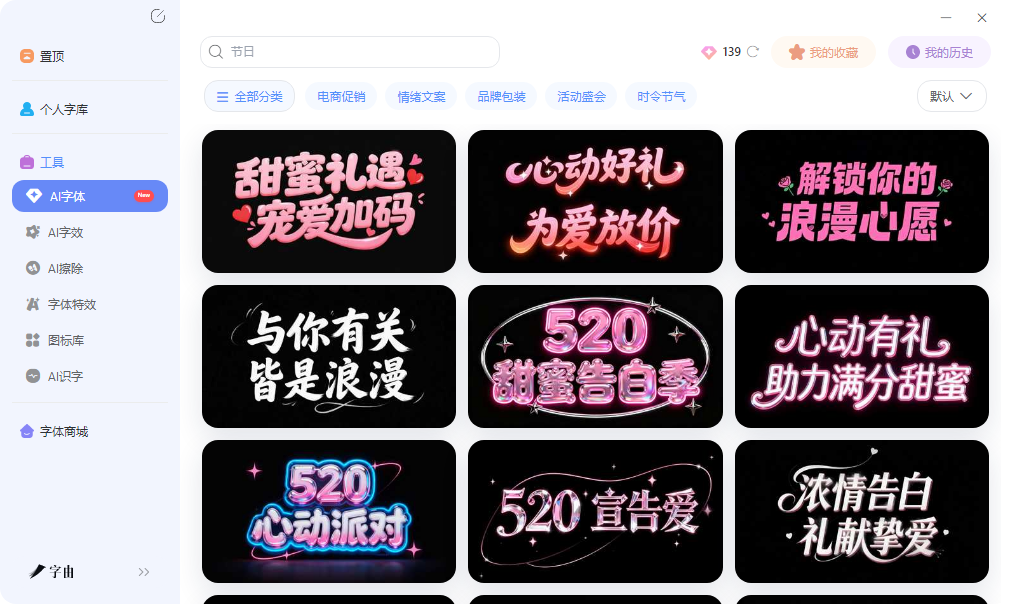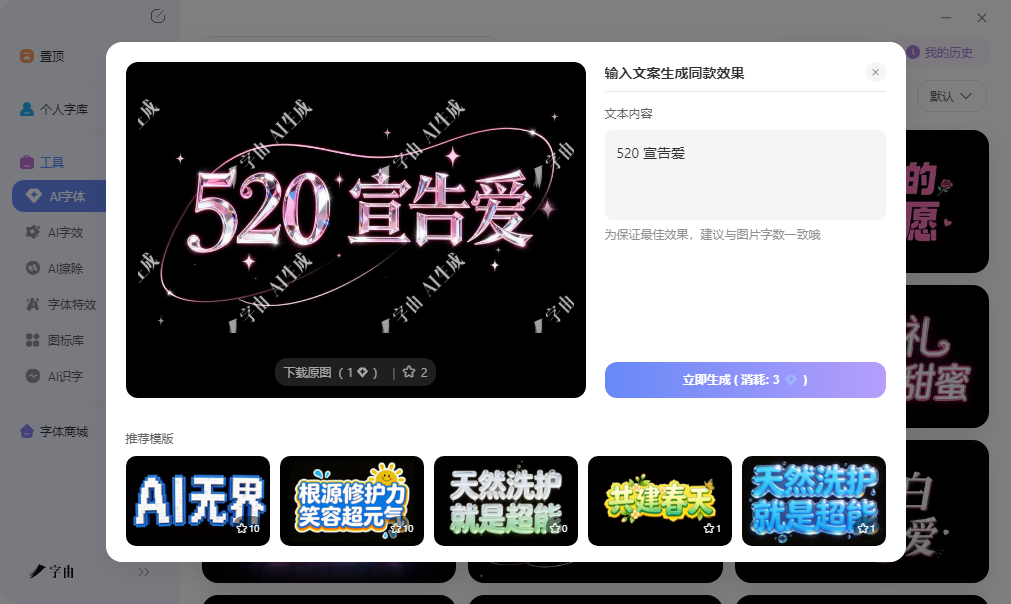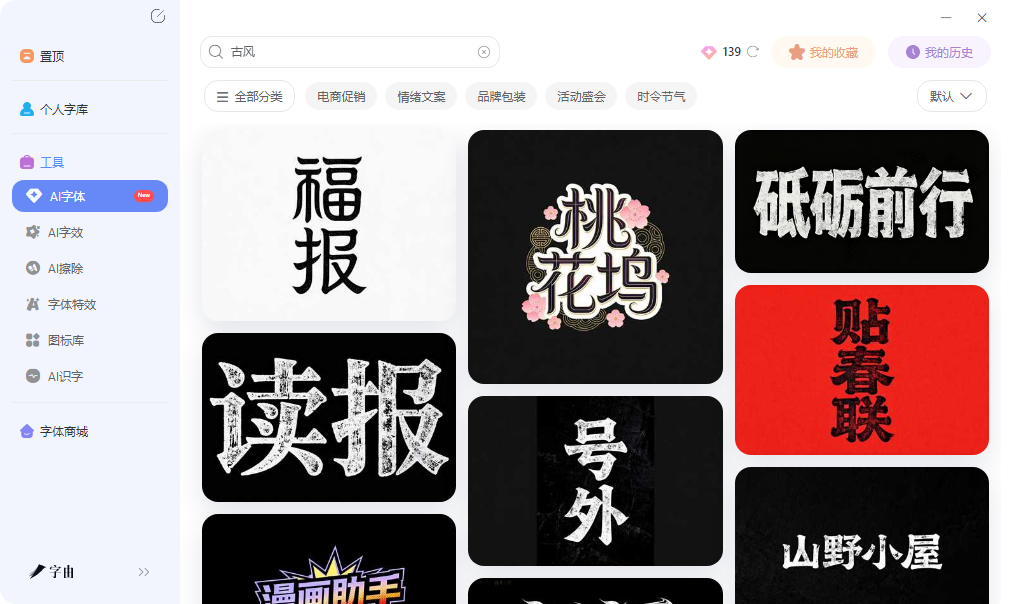
在线字体转换,输入文字直接变花体
现在普通的字体已经不能满足设计的大部分需求了,有时候哪怕不是设计,如果是自己先娱乐一下,普通的字体肯定也是不够看的,花体字这些需求说大不大,但系统自带字体里根本不够用。现在不用担心了,在线字体转换器直接输入文字,选择想要的风格,生成后复制粘贴,所有平台都能正常显示。今天选了5款工具,有的专攻花体英文,有的能玩火星文,有的还支持篆书草书在线预览。大家可以按需选择。
大部分人打开设计软件,卡住的第一步不是“不会调参数”,而是“不知道自己要什么风格”。国潮、霓虹、金属、手写、可爱……脑子里只有一个模糊的感觉,但说不清楚。字由的AI字体模块专门解决这个问题。
打开字由客户端,进入“AI字体”后,左侧有一列风格标签,每个标签背后对应着一整套已经调试好的设计语言。你不用懂“外发光和投影的区别”,也不用纠结“这个渐变角度合不合适”。你只需要问自己一个问题:我的项目应该偏酷一点、暖一点,还是传统一点?点一下对应的标签,所有匹配的模板会自动刷出来。这个动作把“从零开始想方案”变成了“做选择题”,决策成本降了一大截。
比如你正在做一款新中式茶饮的海报标题。你隐约觉得应该有点书法味,但又不想太传统。点一下“国潮风”标签,系统会筛选出几十款融合了书法笔触和现代排版的模板。你可以在这些现成方案里快速浏览,看到顺眼的再生成图片。整个过程几乎没有试错成本。
字由AI字体不需要你从头摸索,这对于电商运营、自媒体小编、或者刚入门的设计师来说,是最值得尝试的内容。
2、网名生成器
第二个网站是一个网名生成器平台。它专门为社交昵称、游戏ID设计,功能非常丰富。页面提供了“火星文转换器”“特效文字生成器”“花样网名生成器”“繁简体转换器”等多个工具。
输入文字后,点击“立即生成”,下面会展示多种特效样式。特效文字生成器可以生成删除线、飞鸟文、花藤文、爱心文、菊花文、尾巴文等——每个字母前后加上小符号,让普通文字变成带装饰的花体。花样网名生成器则提供现成的网名模板,小众高级、不烂大街。火星文转换器可以把简体字转成非主流火星文(如“伱恏”变成“妳好”)。特殊符号推荐模块还能直接复制各种装饰符号(翅膀、星星、爱心等)。
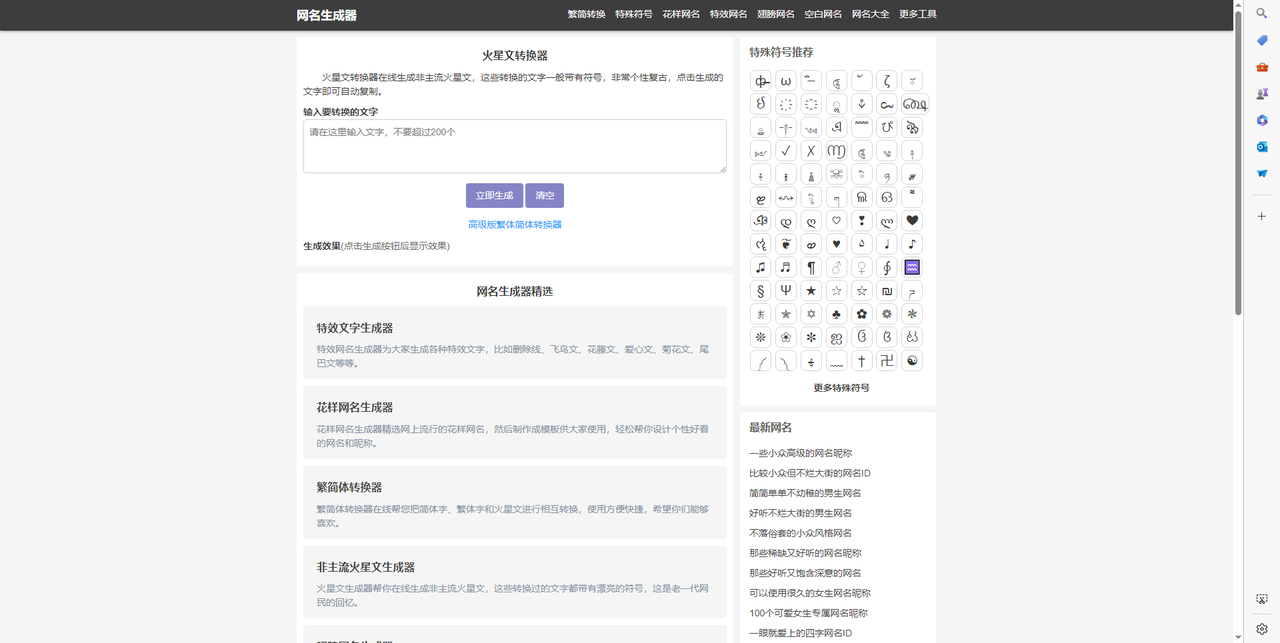
3、美术字
第三个网站是美术字。它不是一个简单的“选模板生成”,而是一个在线文字特效编辑器,自由度很高。页面左侧可以选择字体(默认、经典字体、艺术字体、花体字体、POP体等),中间是画布预览区,右侧可以设置字体大小、颜色、背景宽度/高度、背景透明、填充纹理、背景纹理、背景颜色、渐变方向、横向/纵向间距等参数。
如果你对艺术字有精确要求——颜色必须和品牌色一致、需要渐变背景、文字要旋转某个角度——美术字的参数面板能让你精细控制。比PS简单,又比普通生成器灵活。保存图片前实时预览,调整完直接下载。适合经常做海报、封面、Banner的设计师。
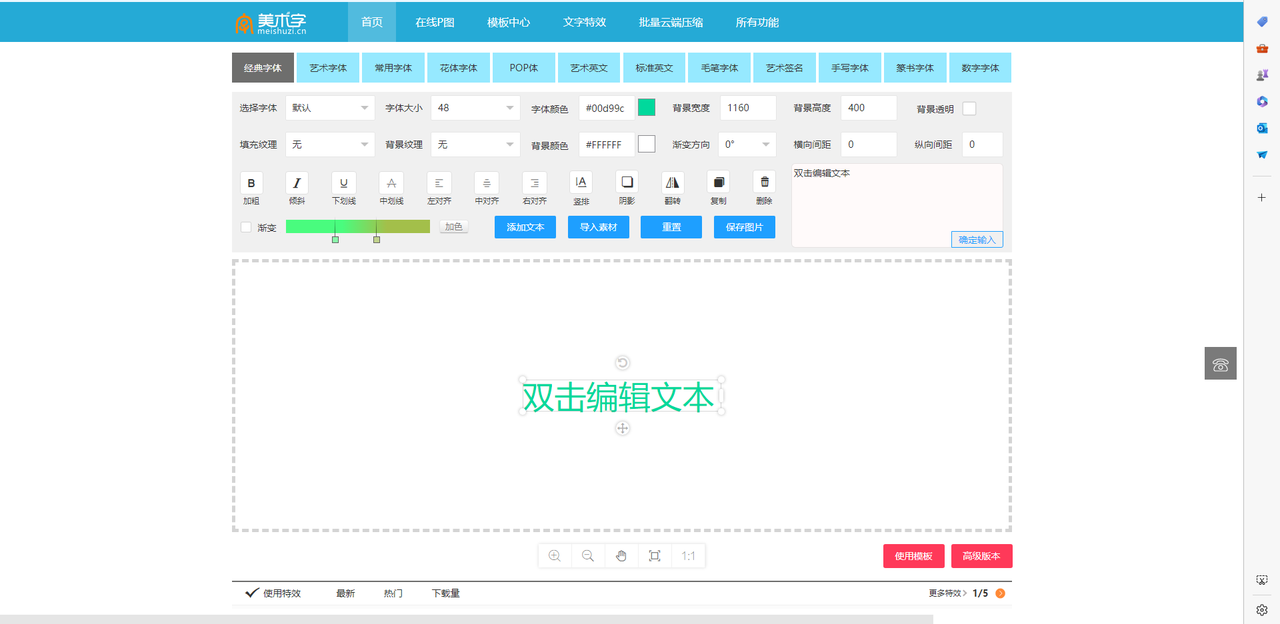
4、千千秀字
第四个网站是千千秀字。它提供了一个“篆书、隶书、楷书、草书、行书字体在线预览”工具。输入文字(5-18字),选择字体(篆书/隶书/楷书/草书/行书),可微调字号(+0/+2/+4),选择背景(白色/黑色/透明/卷轴),点击“点此转换”,下方立即生成预览图片。这个工具最大的特点是将五种主流书法字体集中在一个页面对比展示。你可以输入同一句话,分别看五种字体的效果,快速判断哪种最适合你的项目。页面下方还附带了每种字体的知识简介。如果你在设计Logo、海报时需要对比不同书法风格,或者对书法字体不太熟悉,这个工具能帮你快速建立认知。预览效果清晰,操作简单,完全免费。
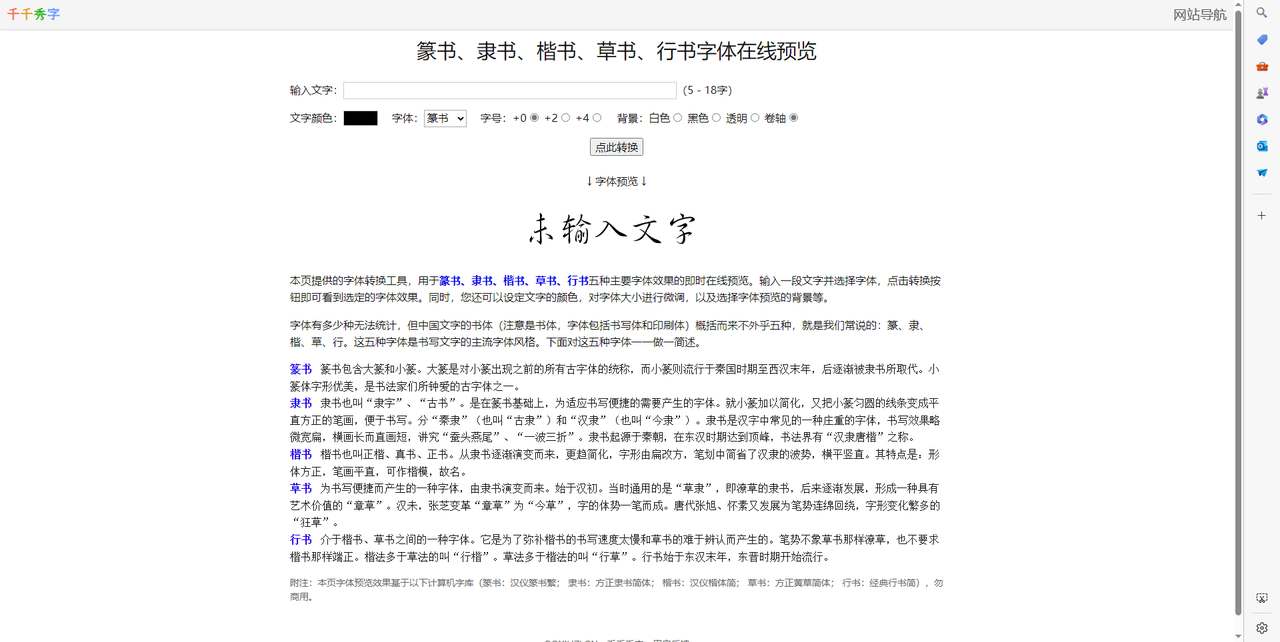
5、字体转换器
第五个网站是一个字体转换器(。界面简洁:输入文字,选择字体(华康娃娃字体、华康海报、华文行楷等),设置输入大小、文字颜色、背景颜色,点击“提交生成”,就能预览转换后的效果。每款字体旁边有“查看使用”链接,可能跳转到字体介绍或下载页面。这个站提供的字体偏向装饰性和趣味性,如“华康娃娃字体”圆润可爱,适合儿童主题;“华文行楷”流畅潇洒,适合中式风格。操作非常直接,没有复杂参数。适合不想折腾设置、只想快速看到某款特定字体效果的用户。生成结果可以截图保存,或参考字体名后在字由等平台激活使用。
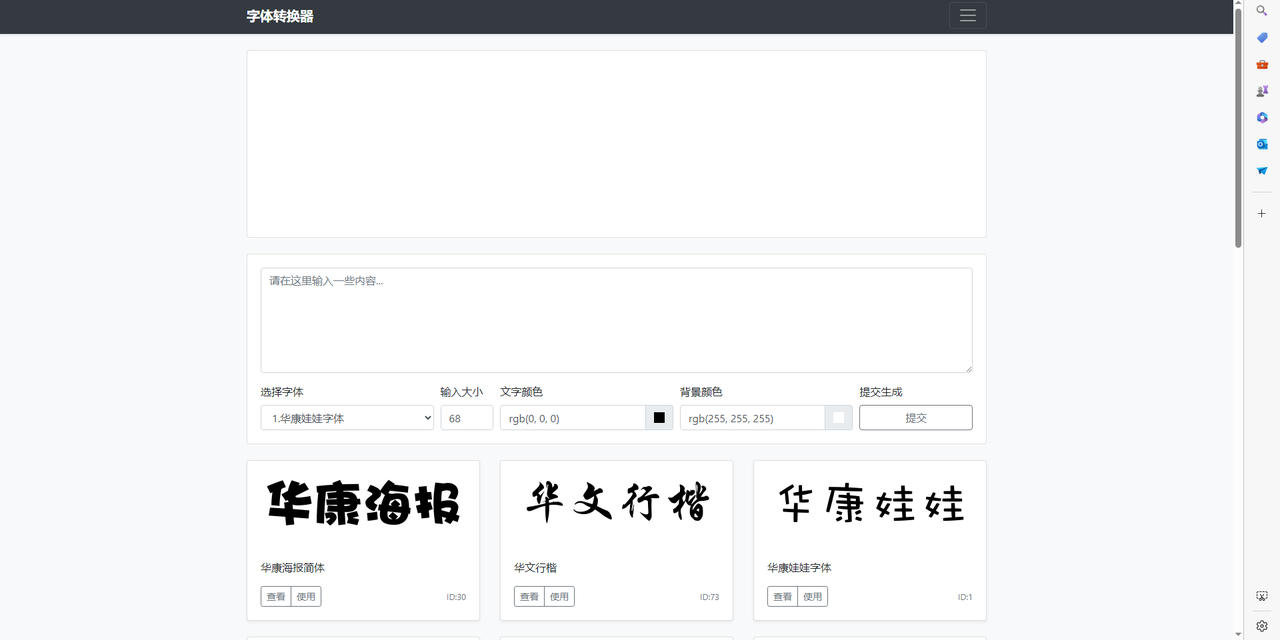
看完这五个工具的介绍相信你心里已经有了选择。字由最适合需要高清艺术字图片的设计师;网名生成器专攻社交昵称,火星文、花藤文、爱心文一键转换,完全免费;美术字参数丰富,可调颜色、渐变、阴影,适合精细控制;千千秀字提供篆隶楷草行五种书法在线预览,适合对比选型;字体转换器简单直接,华康娃娃、华文行楷等字体一键转换。你需要做的只是输入文字,选个喜欢的样式,复制或下载,几秒钟就能用在你的设计或社交账号上。不用下载软件,不用学设计,在线就能搞定。